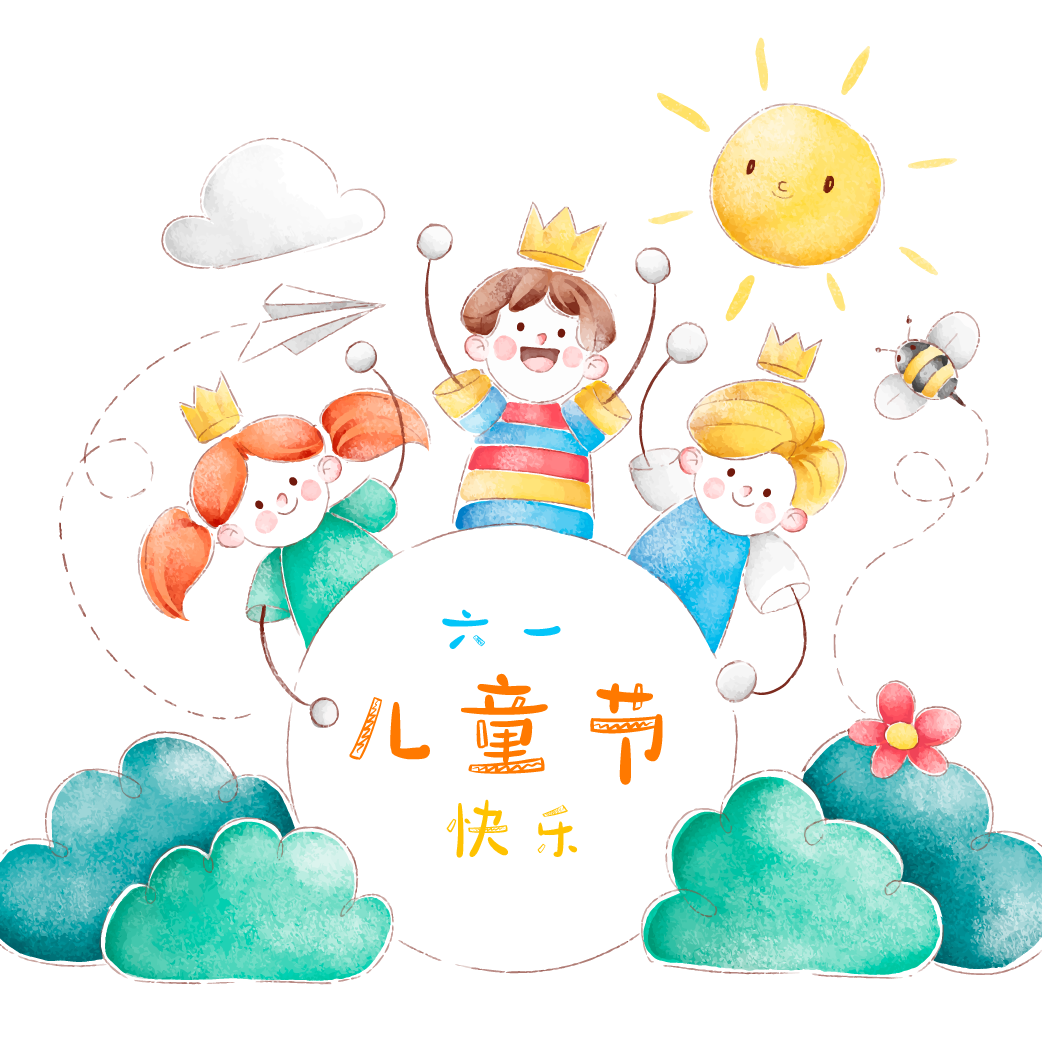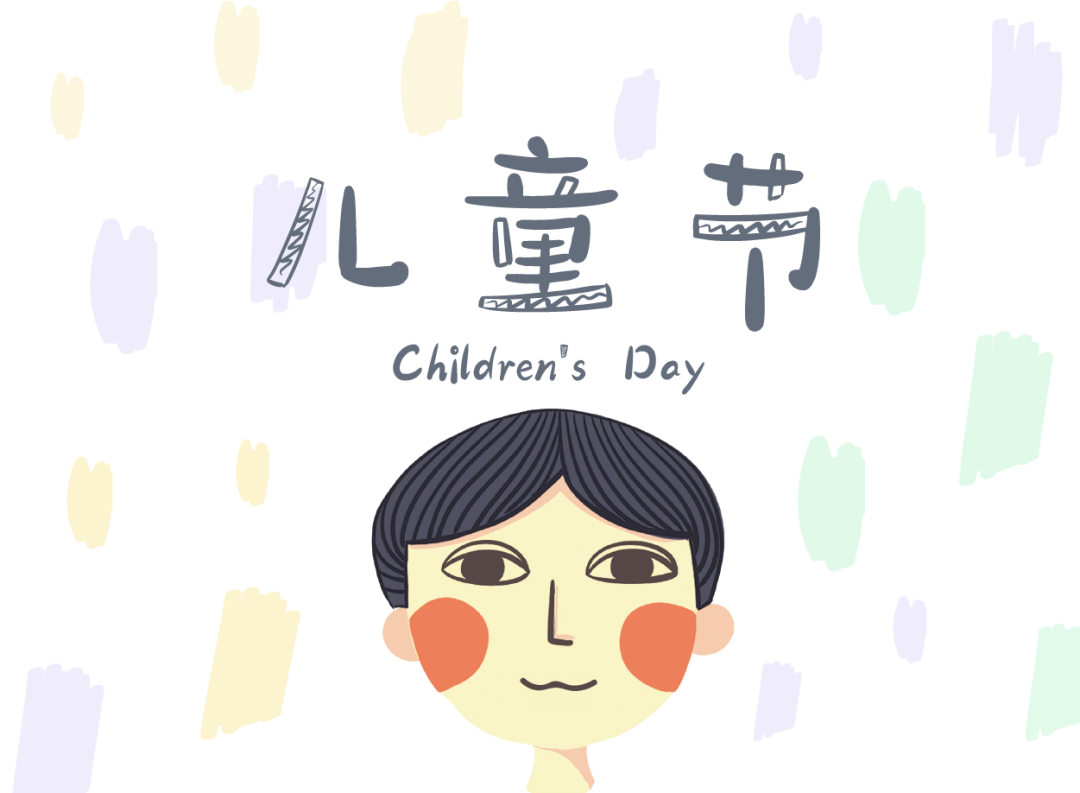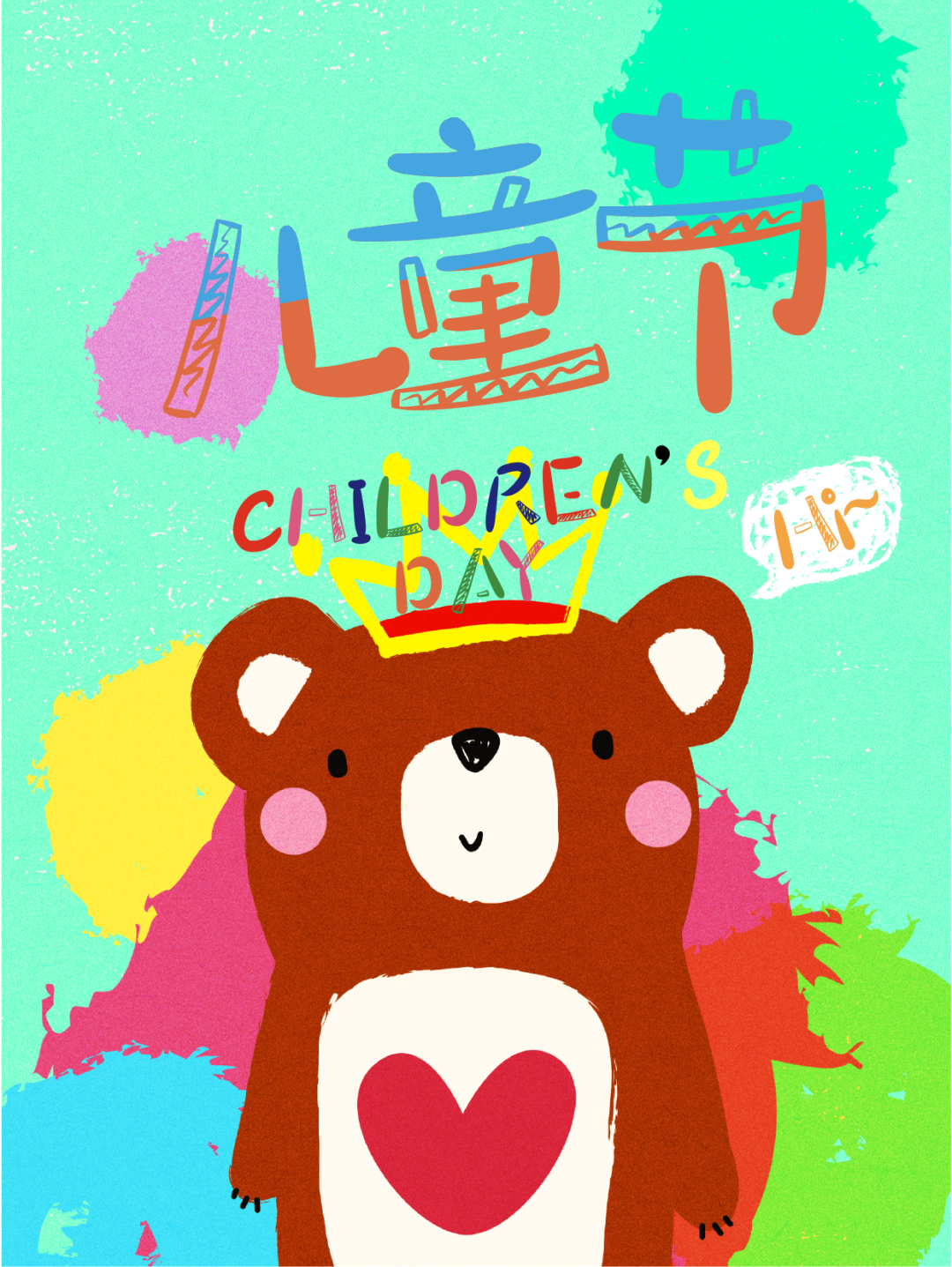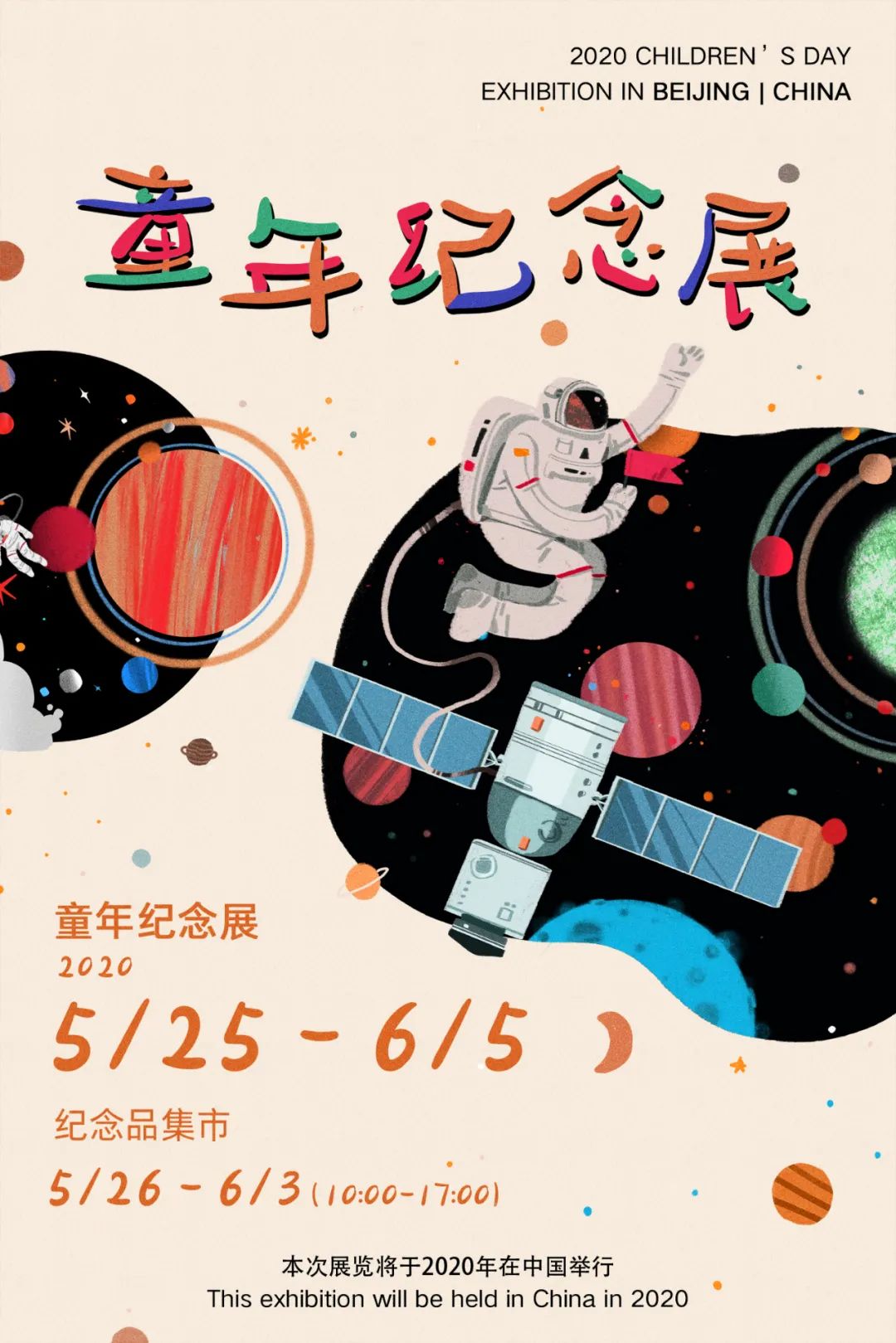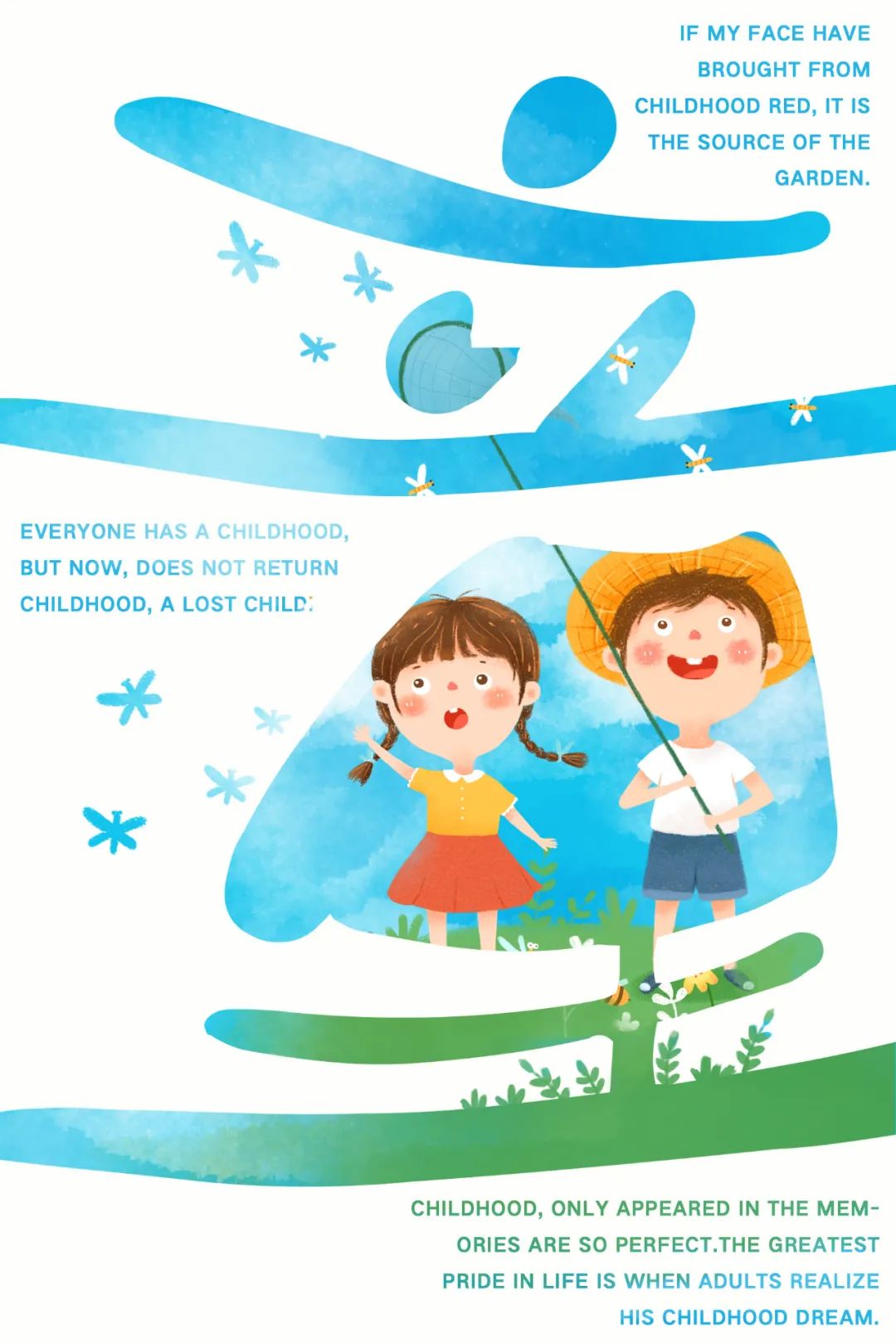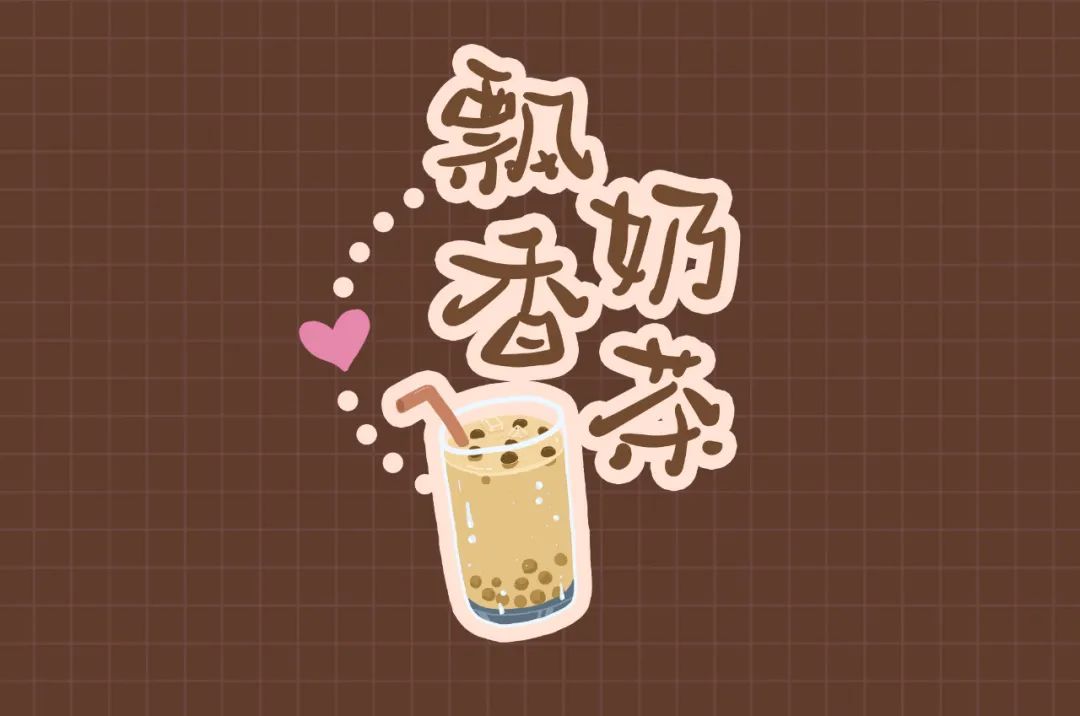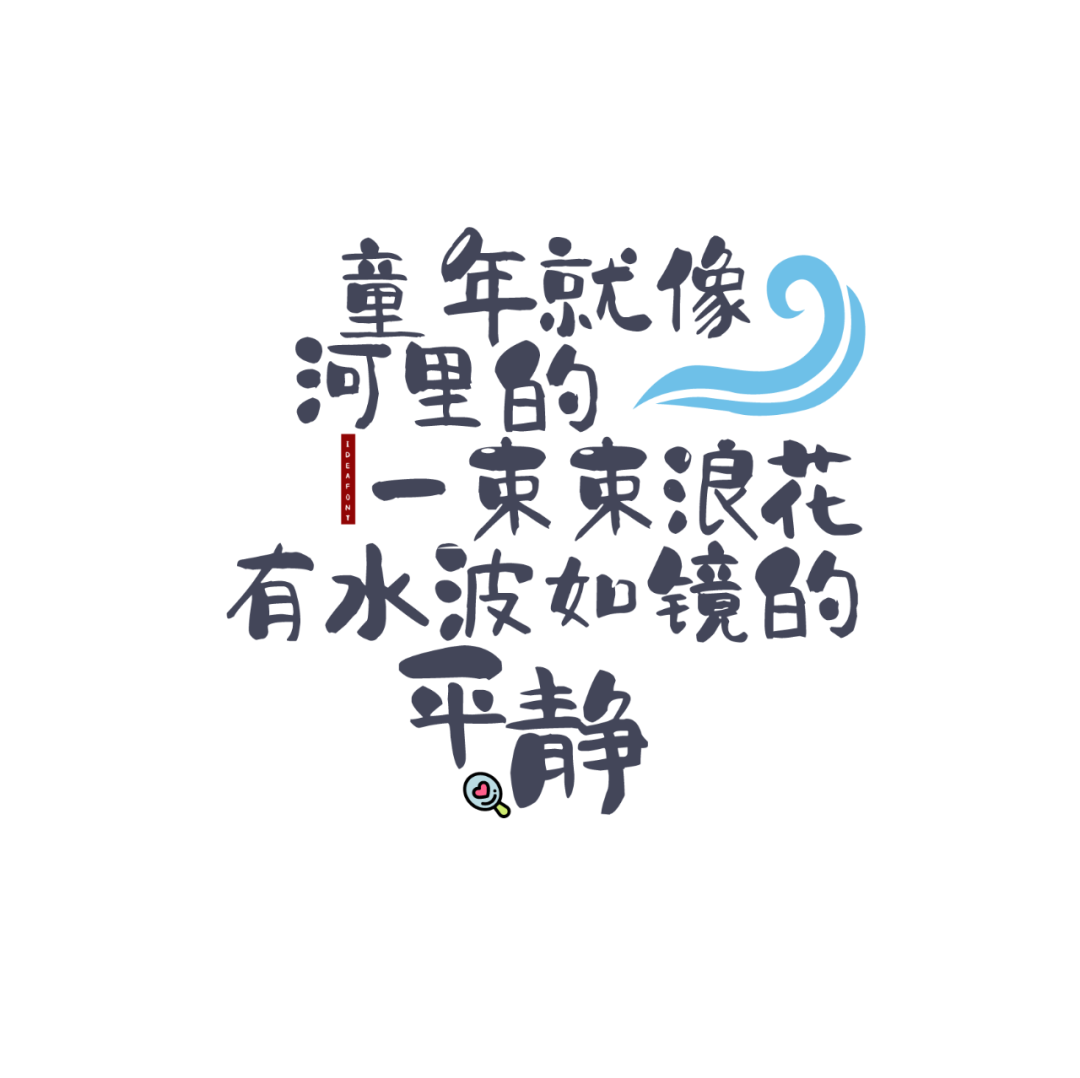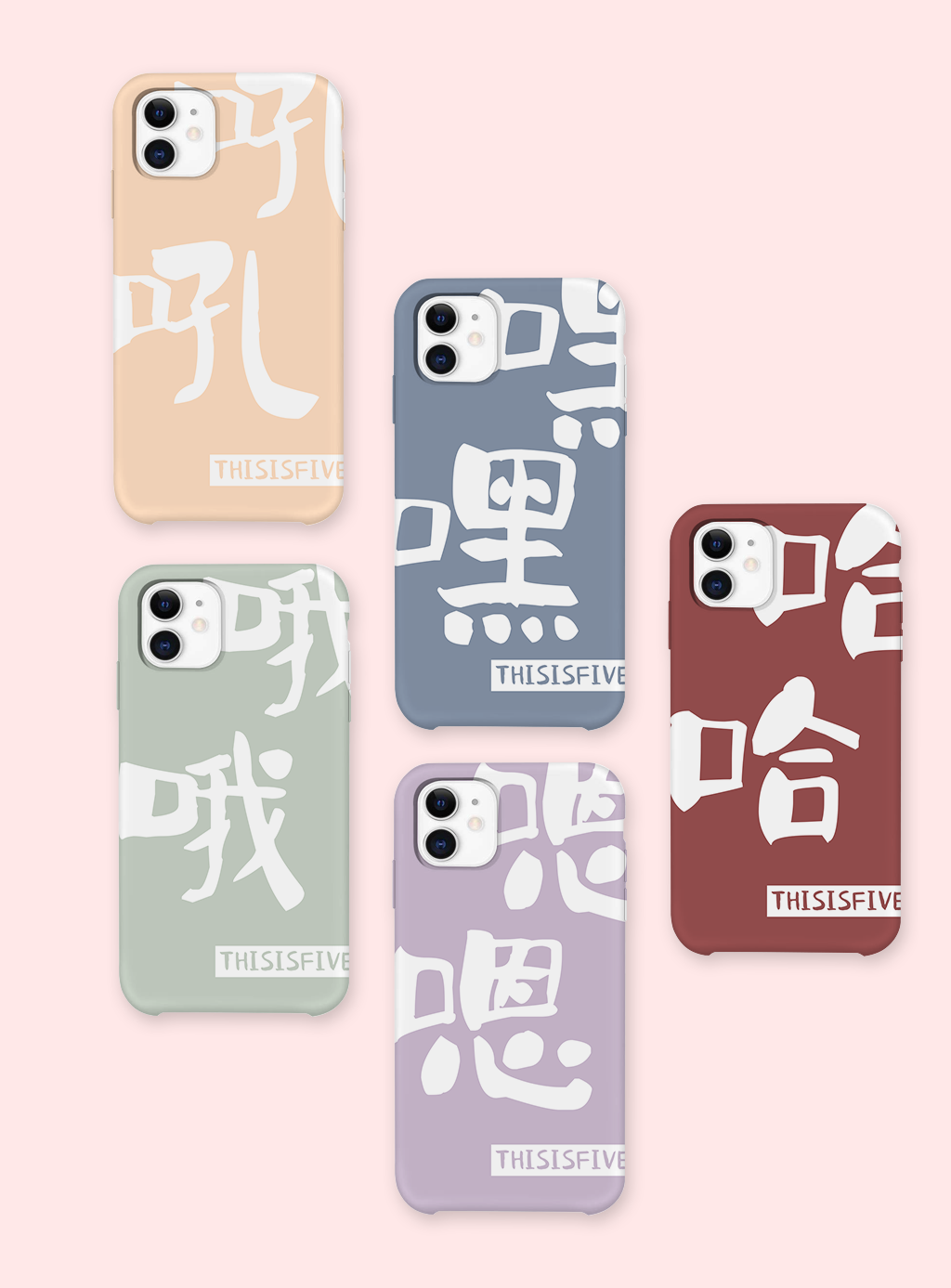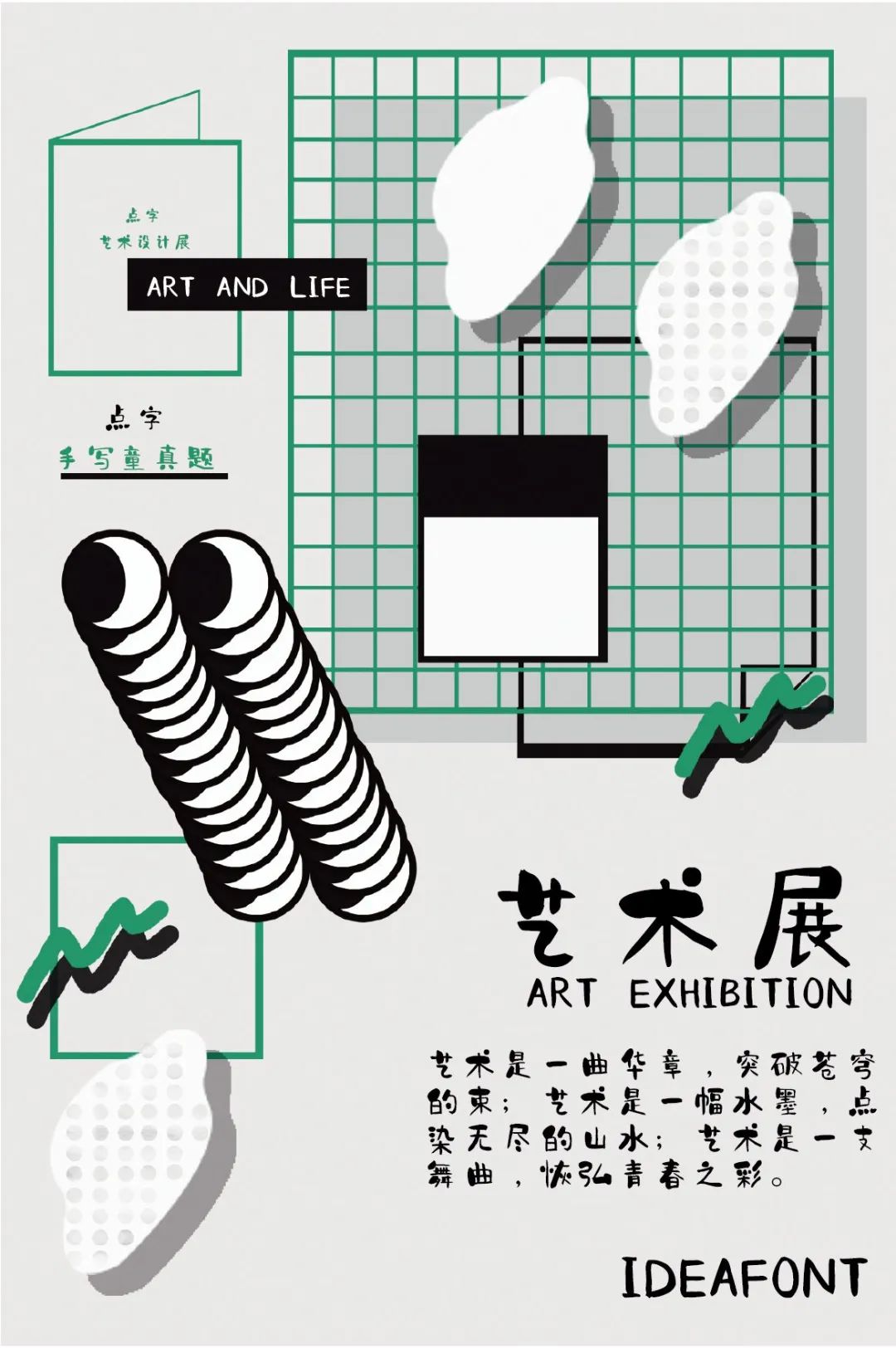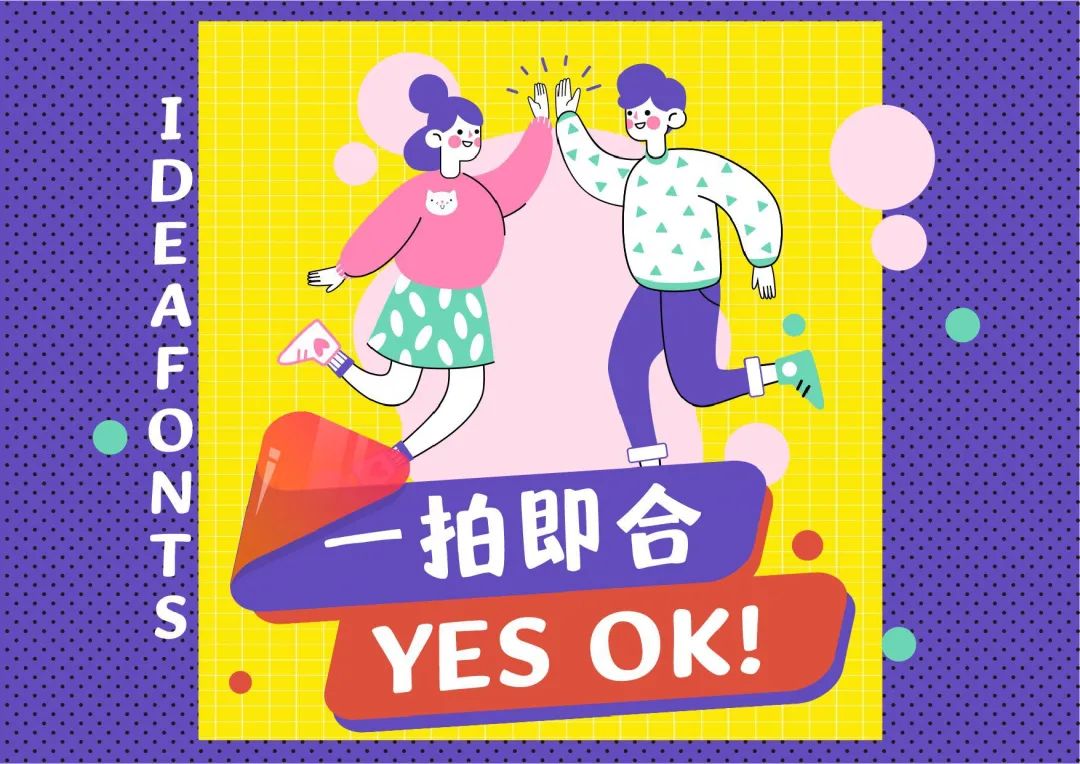
六一儿童节,怎么用字体卖萌?
曾经有无数个儿童节摆在我面前,我没有珍惜,直到失去后才追悔莫及,假如上天再给我一次机会,我会大声说,我想当个宝宝……
点字童稚体
这是一款自带特效的字体,笔触间有着小时候涂鸦的感觉,有了它,你都不用做过多设计,简简单单换个色就很好看了,特别适合马上到来的六一。
点字悠漫体
童年给人的感觉,总是可以任意挥霍,等到长大了,才希望它悠长一点,浪漫一点,所以点字悠漫体就是一款比较“咸鱼”的字体,让你跟着它一起穿越,享受一下慢时光。
点字手写童真体
这是柚子最喜欢的一款字体,感觉专为童年而设计,粗细对比的手写笔触,再加上软萌的气质,可爱得不要不要的。
点字奇妙体
最后是一款轻松可爱的标题字,它的字型就跟名字一样,第一眼就让人好奇,再看一眼就是妙趣横生,不论用在哪,都能让画面亲和度倍增。
今日份儿童节一日游已经到站,有你喜欢的吗?